웹폰트, 지금 당신 사이트엔 필요 없을 수도 있습니다
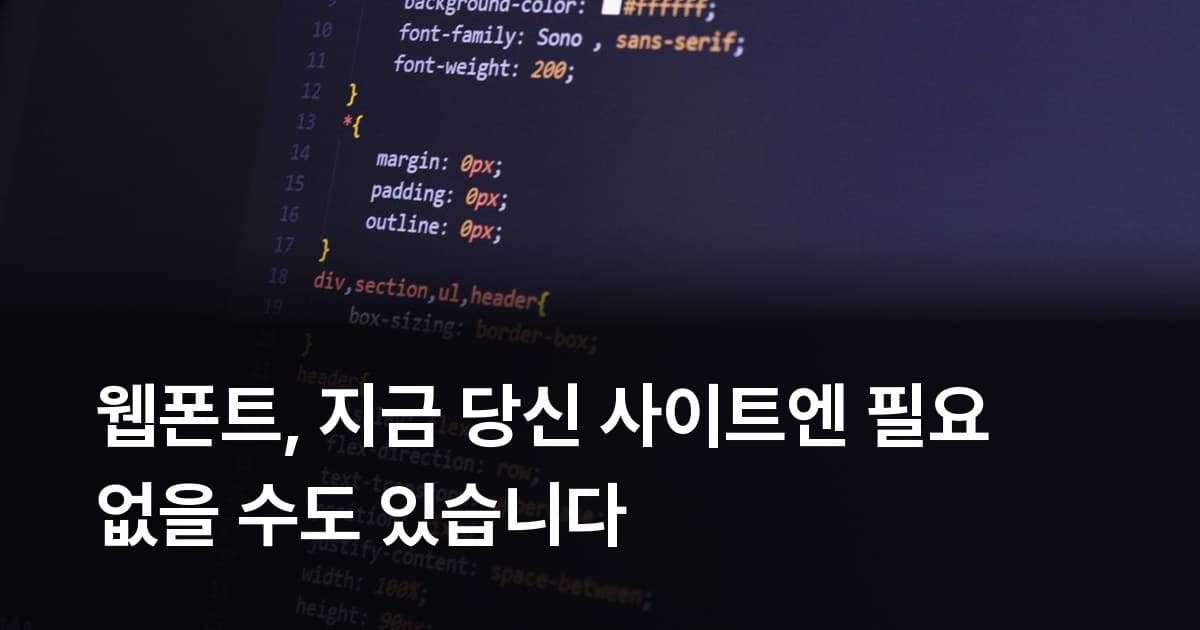
디자인 관련 글을 보다 보면 "웹폰트를 써야 한다"는 전제가 으레 깔려 있습니다. Pretendard를 연결하고, font-display: swap을 설정하고, 서브셋까지 처리하고… 어느 순간 이 과정이 웹 제작의 당연한 루틴처럼 굳어졌어요.
저는 그 전제를 뒤집어 보고 싶습니다.
GitHub, Medium, Bootstrap, Booking.com. 이 서비스들의 공통점이 있습니다. 전부 시스템 폰트 스택을 씁니다. 폰트를 고를 능력이 없어서가 아닙니다. 성능과 유지 관리를 따져본 뒤 의도적으로 안 쓰기로 결정한 겁니다.
웹폰트는 켜는 것보다 끄는 게 기본값이어야 할 기술입니다. 파일 크기, LCP 지연, CLS 위험, 라이선스 관리—이 네 가지 비용을 치르고도 얻는 게 더 많은 상황인지 먼저 확인해야 합니다. 이 글은 그 확인을 돕습니다.
웹폰트 없어도 되는 사이트 유형부터 걸러봅니다
아래 항목 중 해당하는 게 많을수록 시스템 폰트 스택이 더 나은 선택입니다. 웹폰트를 어떻게 쓸까 고민하기 전에, 진짜 필요한지부터 따져보세요.
사이트 성격
- 개인 블로그 또는 기술 블로그
- 개인 포트폴리오 사이트
- 회사 내부 인트라넷·어드민 대시보드
- 단순 랜딩페이지 (정보 전달 위주, 마케팅 페이지 아님)
- 문서 사이트·개발자 레퍼런스 페이지
- Core Web Vitals 점수 개선이 필요한 사이트
운영 상황
- 모바일 성능이 최우선인 서비스
- 느린 네트워크 환경 사용자가 많은 서비스
- 폰트 라이선스 관리가 번거롭게 느껴지는 상황
- 웹폰트 적용 후 CLS가 눈에 띄게 올라간 경우
- 빠른 프로토타입·MVP 단계여서 폰트 설정에 시간 쓰기 아까운 경우
디자인 방향
- 특정 서체 브랜딩보다 콘텐츠 가독성이 더 중요한 경우
- OS 네이티브 느낌이 오히려 신뢰감을 주는 서비스 (관리도구, SaaS 대시보드 등)
- 다국어 지원이 필요하고 무거운 폰트를 서브셋 없이 쓰고 싶지 않은 경우
5개 이상 해당한다면 웹폰트 없이 시스템 폰트 스택만으로 시작하는 걸 진지하게 고려해볼 만합니다. 브랜딩이 확립된 이후에 추가해도 늦지 않고, 오히려 그쪽이 더 깔끔한 순서입니다.
현실적으로 생각해보면, 개인 블로그나 포트폴리오처럼 콘텐츠가 주인공인 사이트에서 폰트를 바꾼다고 독자가 체감하는 경우는 드뭅니다. 반면 Lighthouse에서 LCP가 개선되는 건 숫자로 바로 보입니다. 개선 효과가 명확한 쪽을 고르는 게 합리적입니다.
웹폰트가 실제로 치르는 비용, 숫자로 보면 이렇습니다
체크리스트를 봤는데도 "그래도 한번 써볼까" 싶다면, 비용부터 숫자로 보세요.
한글 웹폰트는 특히 무겁습니다. 영문 폰트는 수십 KB 수준이지만, 한글은 1만 1,172자를 커버해야 하기 때문에 최적화 없이는 수백 KB에서 수 MB까지 올라갑니다. WOFF2 압축·서브셋 처리를 해도 영문보다 수배 무거운 건 구조적인 문제입니다. HTTP Archive 2024 Web Almanac 기준으로 데스크톱 페이지의 폰트 중앙값은 약 131KB로, 전체 페이지 무게(데스크톱 중앙값 약 1,895KB)의 약 7% 수준입니다. 평균치만 보면 얌전해 보이지만, 최적화 없는 한글 폰트는 그 몇 배를 훌쩍 넘기기 때문에 다릅니다.
성능 관점에서 두 가지 문제가 구체적으로 나타납니다.
LCP(Largest Contentful Paint) 지연. 폰트 파일을 받는 동안 텍스트 렌더링이 늦어집니다. 기본값(font-display: block)은 최대 3초까지 텍스트를 숨깁니다. font-display: swap을 쓰면 일단 시스템 폰트로 보여주지만, 네트워크 요청 자체는 그대로입니다.
CLS(Cumulative Layout Shift) 위험. font-display: swap을 쓸 경우, 시스템 폰트로 먼저 뜬 텍스트가 웹폰트 로드 후 교체되면서 글자 너비와 행간이 달라집니다. 레이아웃이 밀리거나 버튼 크기가 바뀌는 현상이 여기서 납니다. CLS는 Google Core Web Vitals에서 검색 순위에 직접 영향을 주는 지표입니다.
웹폰트 vs 시스템 폰트 스택 성능 비교
| 항목 | 시스템 폰트 스택 | 웹폰트 |
|---|---|---|
| 네트워크 요청 | 없음 | 폰트 파일 다운로드 필수 |
| LCP 영향 | 없음 | 다운로드 시간만큼 지연 |
| CLS 위험 | 없음 | font-display: swap 사용 시 레이아웃 이동 발생 가능 |
| 한글 폰트 용량 | 0 KB | 수백 KB~수 MB (서브셋 처리 후에도 수십 KB 이상) |
| OS별 외관 차이 | 있음 (기기마다 다른 폰트) | 없음 (모든 기기에서 동일) |
| 브랜드 표현력 | 제한적 | 높음 |
| 유지 관리 | 없음 | 라이선스 갱신·CDN 의존성 관리 필요 |
시스템 폰트 스택, 이 정도면 충분합니다
웹폰트를 안 쓰는 게 곧 포기가 아닙니다. 시스템 폰트 스택은 기기에 이미 설치된 폰트를 우선 쓰도록 CSS에 명시하는 방법입니다. 네트워크 요청이 없고, 기기에 최적화된 폰트가 바로 렌더링됩니다. macOS라면 San Francisco, Windows라면 Segoe UI, Android라면 Roboto가 뜹니다.
고해상도 디스플레이 환경에서는 시스템 폰트가 오히려 더 선명하게 보이는 경우도 있습니다. Apple의 San Francisco나 Microsoft의 Segoe UI는 Retina·HiDPI 화면에 맞춰 힌팅이 정교하게 조정된 폰트들이거든요.
가장 많이 쓰이는 현대적 스택:
body {
font-family: system-ui, "Segoe UI", Roboto, Helvetica, Arial,
sans-serif, "Apple Color Emoji", "Segoe UI Emoji";
}
| 폰트 | 대응 환경 |
|---|---|
system-ui |
최신 Chrome·Safari (macOS San Francisco, Windows Segoe UI 자동 선택) |
Segoe UI |
Windows Vista 이상 |
Roboto |
Android 4.0 이상 |
Helvetica / Arial |
macOS·Linux 폴백 |
CSS 변수로 관리하면 나중에 폰트를 바꿀 때도 한 줄만 고치면 됩니다:
:root {
--font-sans: system-ui, "Segoe UI", Roboto, Helvetica, Arial, sans-serif;
}
body {
font-family: var(--font-sans);
}
코드 블록처럼 모노스페이스가 필요한 경우도 따로 웹폰트를 안 써도 됩니다:
code, pre {
font-family: Menlo, Consolas, Monaco, "Liberation Mono", monospace;
}
개발 블로그나 기술 문서 사이트라면 이 정도면 충분합니다. -apple-system, BlinkMacSystemFont는 구형 Safari·Chrome 호환용이라 레거시 지원이 필요한 경우에만 앞에 추가하면 됩니다.
웹폰트가 정말 필요한 경우는 이 정도입니다
여기까지 읽고도 웹폰트가 필요하다는 결론이 나왔다면, 그 판단이 맞는 경우가 실제로 있습니다.
브랜드 정체성이 폰트에 달린 경우. 특정 서체가 브랜드 아이덴티티의 핵심이라면 시스템 폰트로는 대체가 안 됩니다. 로고 주변 텍스트, 헤드라인, 마케팅 페이지처럼 첫인상이 결정적인 영역이 여기 해당합니다.
디자인 일관성이 필수인 경우. 시스템 폰트는 macOS에서는 San Francisco, Windows에서는 Segoe UI로 다르게 뜹니다. 모든 환경에서 동일하게 보여야 하는 서비스라면 웹폰트가 필요합니다.
특수 서체가 꼭 필요한 경우. 손글씨 느낌이나 독특한 디스플레이 타이포그래피는 시스템 폰트로는 구현이 안 됩니다. 굿즈·인쇄물과 웹을 일관성 있게 맞춰야 하는 경우도 마찬가지입니다.
다국어·특수 글리프가 필요한 경우. 아랍어·히브리어·태국어처럼 시스템 폰트 커버리지가 불안정한 언어라면 Noto Sans 계열 웹폰트가 안전합니다.
쓰기로 결정했다면 성능 영향을 줄이는 방법을 함께 챙기세요. WOFF2 형식에 서브셋 처리를 조합하면 파일 크기를 크게 줄일 수 있고, font-display: optional을 적용하면 CLS를 제로로 만들 수 있습니다. 한글은 KS 완성형 기준 자주 쓰는 2,350자만 서브셋으로 추리면 수십~수백 KB 수준으로 내려옵니다. Google Fonts 한국어 옵션은 실제 페이지에 나오는 글자만 동적으로 요청하는 방식이라 자체 호스팅 시에는 직접 정적 서브셋을 만들어야 합니다.
한 가지 더. font-display: optional이라는 중간 선택지도 있습니다. 100ms 안에 폰트가 로드되면 사용하고, 그러지 못하면 그냥 시스템 폰트로 렌더링합니다. CLS도 없고 텍스트 숨김도 없습니다. 느린 모바일 환경에서는 사실상 항상 시스템 폰트가 뜨니, 성능 타협을 최소화하면서 웹폰트를 유지하고 싶다면 고려해볼 값입니다.
웹폰트를 쓰기로 했다면, 선택 전에 꼭 확인할 것
웹폰트 도입 전에 위의 체크리스트로 정말 필요한지 먼저 확인하고, 필요하다는 결론이 나면 그때 신중하게 폰트를 고르는 게 자연스러운 순서입니다.